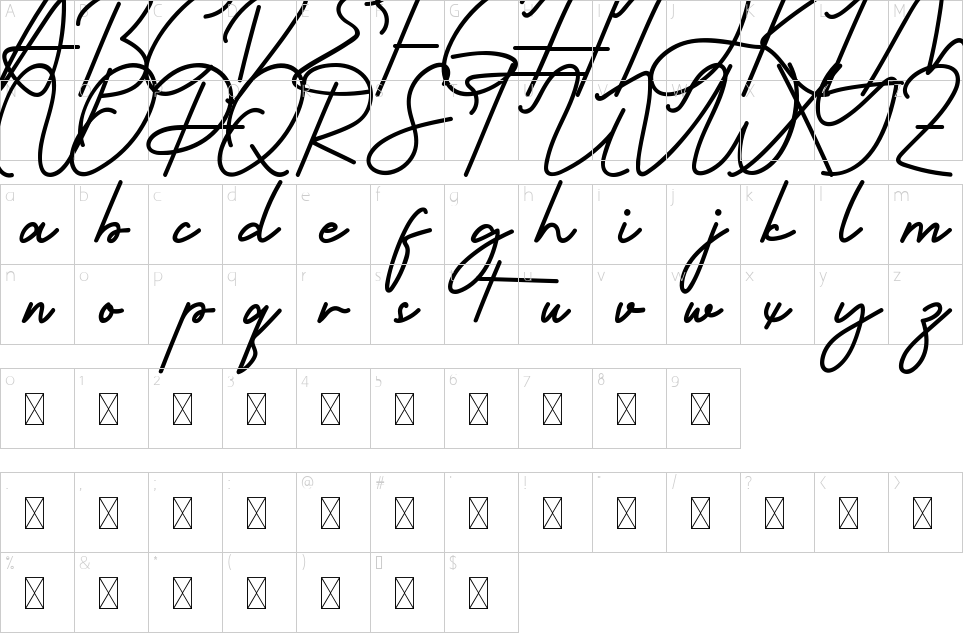
A fonte Seaways é uma opção ótima para designers que buscam uma fonte gráfica e moderna para suas criações. Desenhada por EdricStudio, Seaways oferece um visual agradável e versátil que se adaptará perfeitamente para uma variedade de projetos. Ela está disponível tanto para sistemas Windows quanto para Mac, tornando-a uma fonte versátil e versátil. A fonte Seaways já foi baixada 3.863 vezes, o que a destaca como uma opção popular entre os criadores de conteúdo. Se você está procurando por uma fonte de qualidade para seus projetos de design, Seaways pode ser uma excelente escolha.